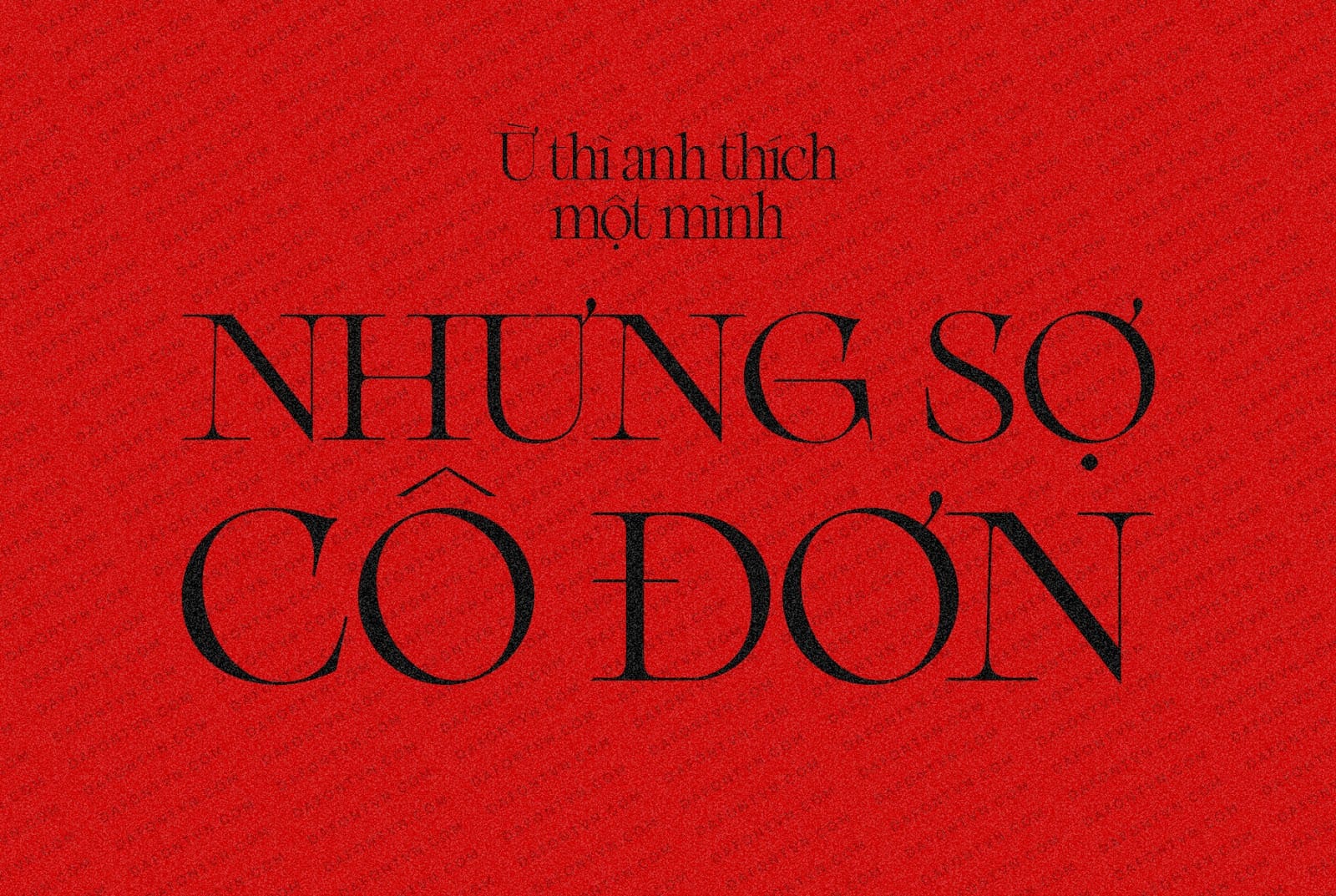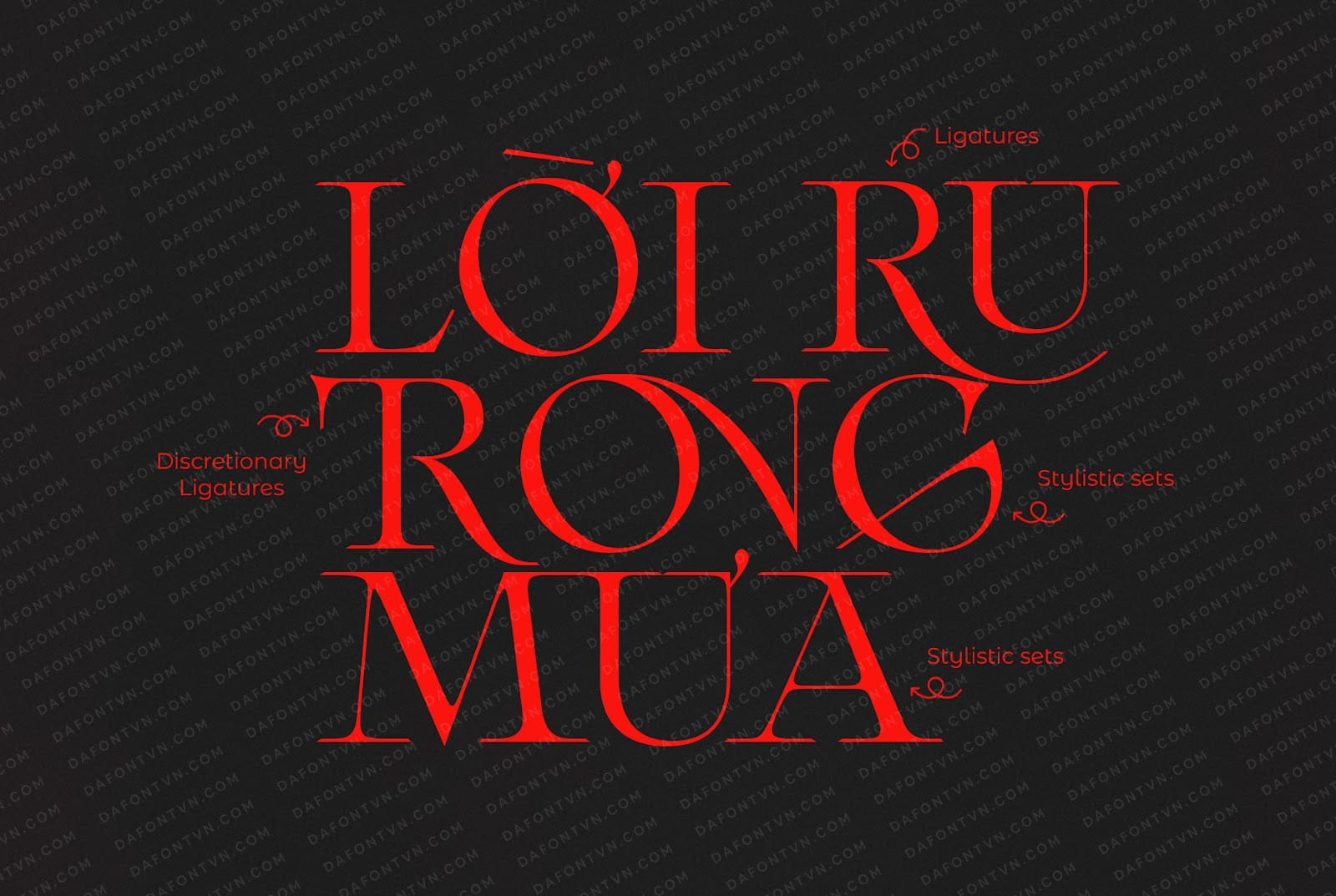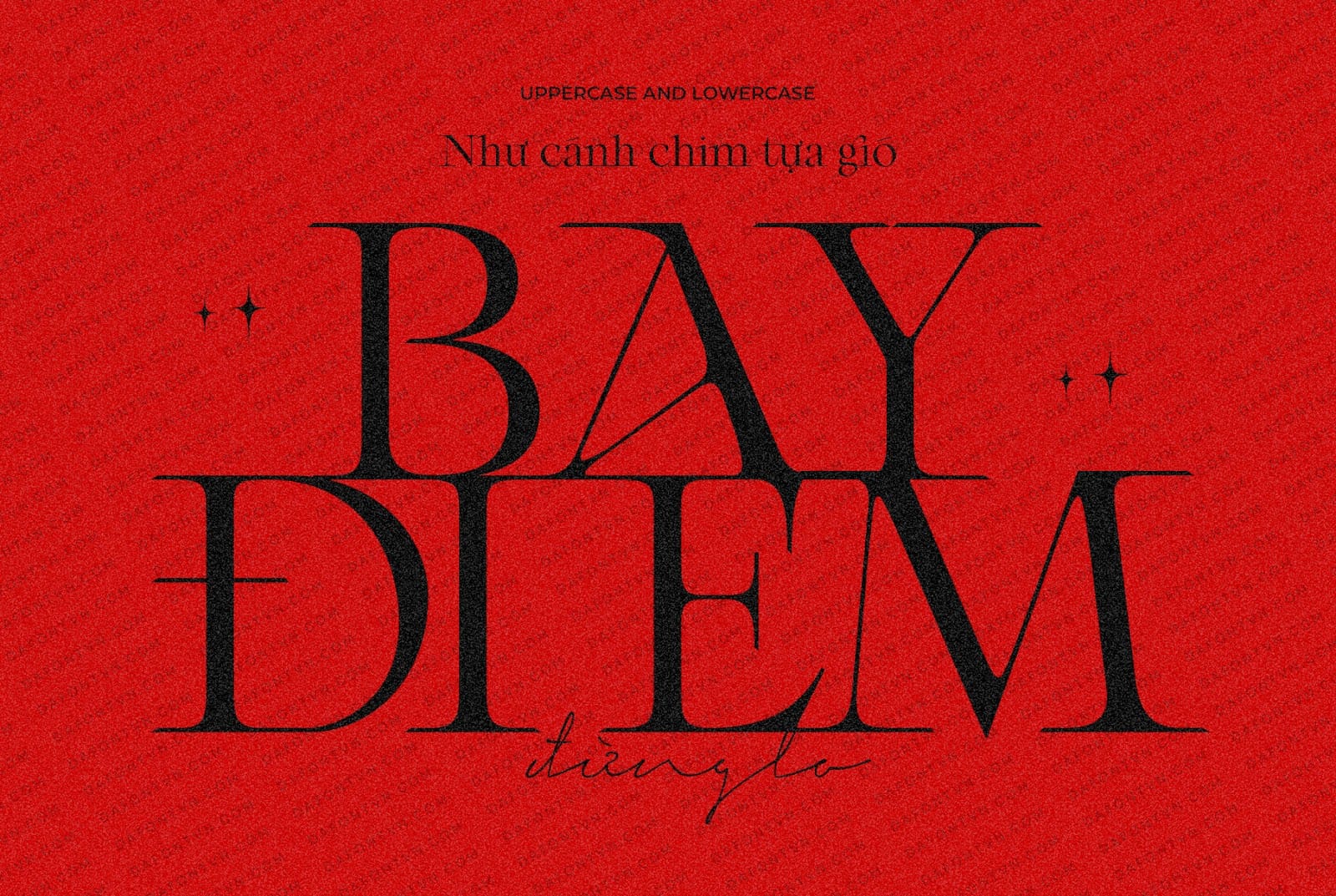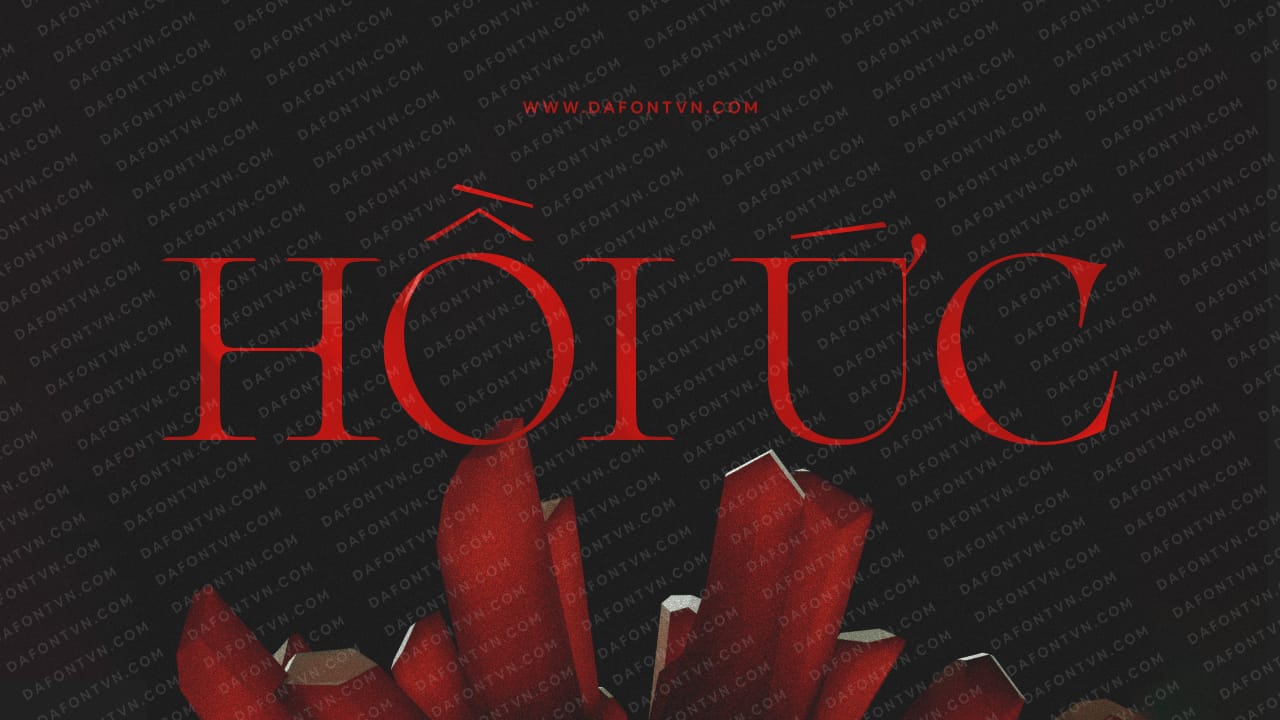
Arthemys Display là một kiểu chữ serif được thiết kế vô cùng độc đáo với các chi tiết tỉ mỉ và hào phóng. Dựa trên thẩm mỹ của thế kỷ 18, nó được sinh ra từ sự kết hợp giữa mẫu vật của Nicolas Grando và các chữ cái khắc trên bản đồ.
Được thiết kế để hiển thị, kiểu chữ này nhấn mạnh sự kết hợp độc đáo giữa các hình dạng từ quá khứ và đương đại, nó làm nổi bật sự nhảy cảm của hai thời đại. Đặc điểm đồ họa của Arthemys cho phép bất kỳ văn bản nào cũng có được giá trị vừa hiện đại, tinh tế và nổi bật.
Các nét chữ được thiết kế vô cùng ấn tượng của Arthemys sẽ mang đến cho bất kỳ dự án thiết kế nào của bạn một vẻ ngoài tinh tế và đẹp mắt. Bạn có thể sử dụng nó cho các thiết kế như: tiêu đề, tạp chí, bìa sách, poster hoặc cũng có thể sử dụng trong các thiết kế mang phong cách retro.